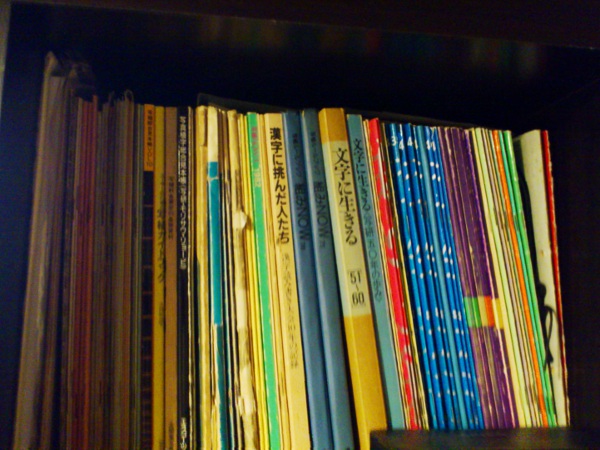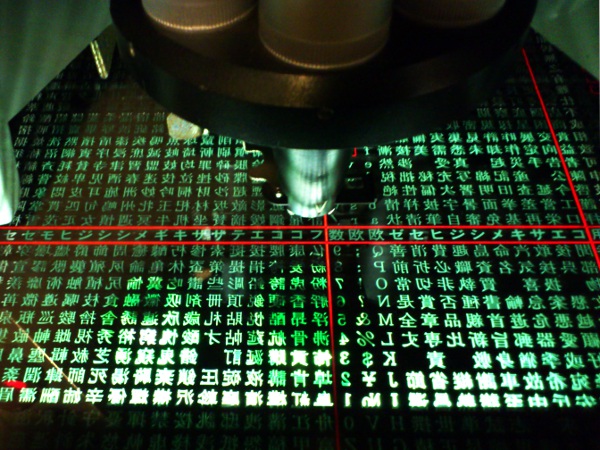
サマースクール・亮月写植室見学会に行ってきた ―後篇
写植室の中をあれこれ見学
写植を打ち終えたら次の方に交替し、その間に写植室にあるものをいろいろ見せていただいた。
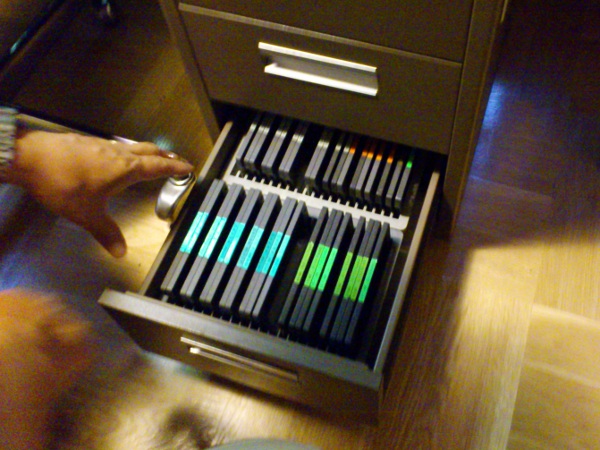
机の引き出しにしまってあるこれは文字盤のサブプレート。これは亮月写植室にある文字盤のほんの一部で、ほかの場所にメインプレート・サブプレートともにどっさり保管されていてびっくり。
写植に関する資料も盛りだくさんで、この写真にあるのはこれまたほんの一部。書体見本帳はもちろんのこと、写植機の説明書、写研の機関紙、『文字に生きる』『組みNOW』といった有名な本に至るまで、貴重な資料が揃っている。亮月写植室に泊まり込んで徹夜で読み漁りたいレベル。
これは文字盤(メインプレート)を写植機にセットしたところ。光源に照らされた文字が緑に浮かび上がってなにこれちょうかっこいい。この文字盤の配列はちょっと特殊で、イロハ順になっている。
そんなこんなしているうちに写植が全員分打ちあがり、亮月さんは現像するために暗室へ。数分後には、A4サイズの印画紙に打った文字がくっきり綺麗に印字されていた。意外と速い。
勉強会でのお話
見学が終わった後はセラトピア土岐の会議室に戻り、勉強会。まずは亮月さんのお話から。文字への目覚めや書体との出会い、そして写植ファンとしての半生など、いろいろなエピソードを交えて熱く語られた。写植への情熱はもちろんのこと、その情熱ゆえの内なる葛藤。のほほんと文字好きをやっている私にとってはいろいろと衝撃的だった。
モリサワのHi-Fi文字盤の話など、技術的に面白そうな内容も多々あったが、いちばん印象に残ったのは亮月さんの「写植には血が通っていると思う」という言葉。
サマースクールを終えて
このサマースクールへの参加を決めたのは、実は2日前のことだった。大阪人でもないしDTP関係者でもないし……と迷っていたのだが(笑)、サマースクールから帰ってきて振り返ってみると、やっぱり参加して正解だった。今回のメインである写植室の見学も面白かったし(もっとあの場にいたかったけど!)、発表会や懇親会でのいろいろなお話も新鮮だった。